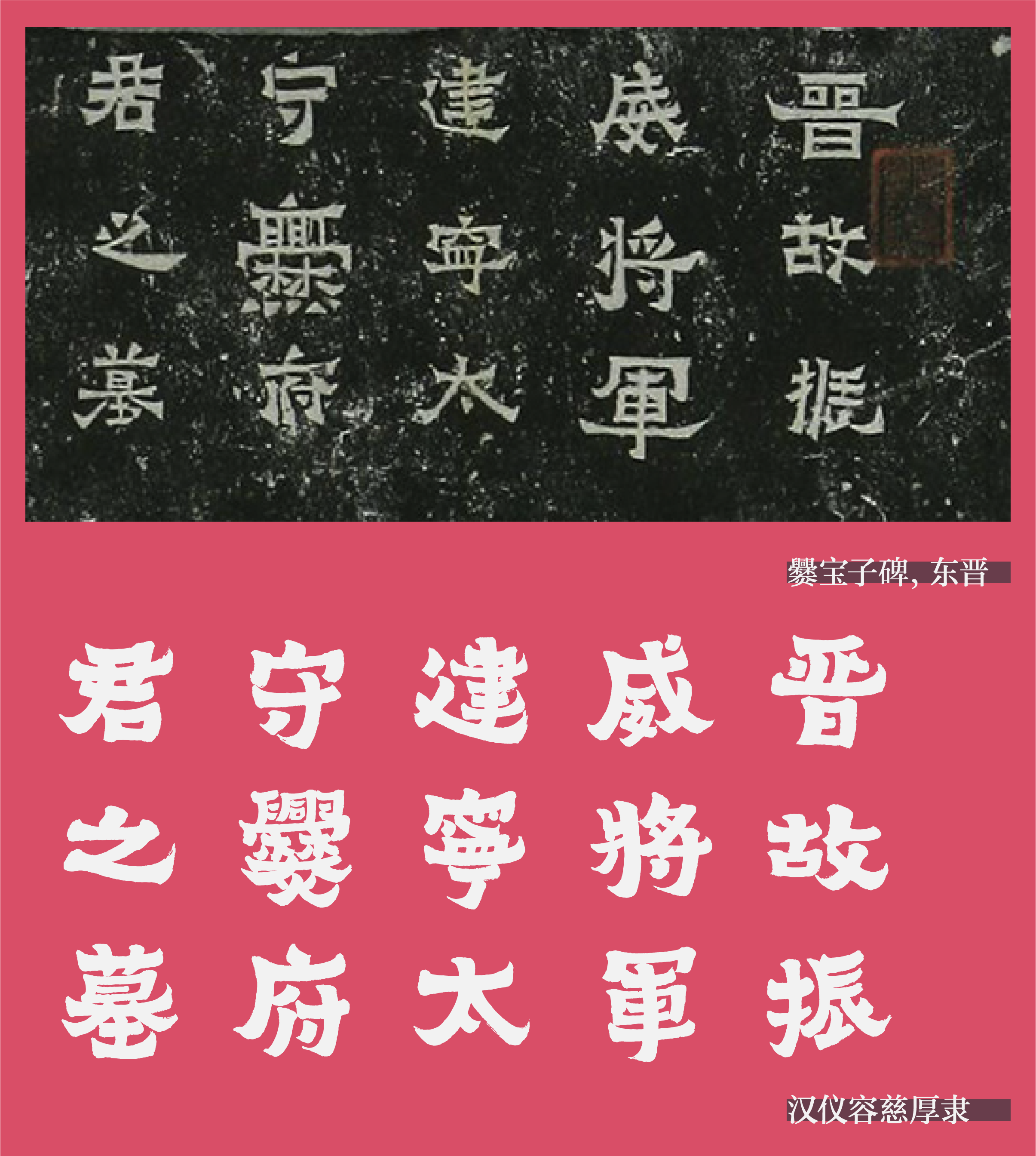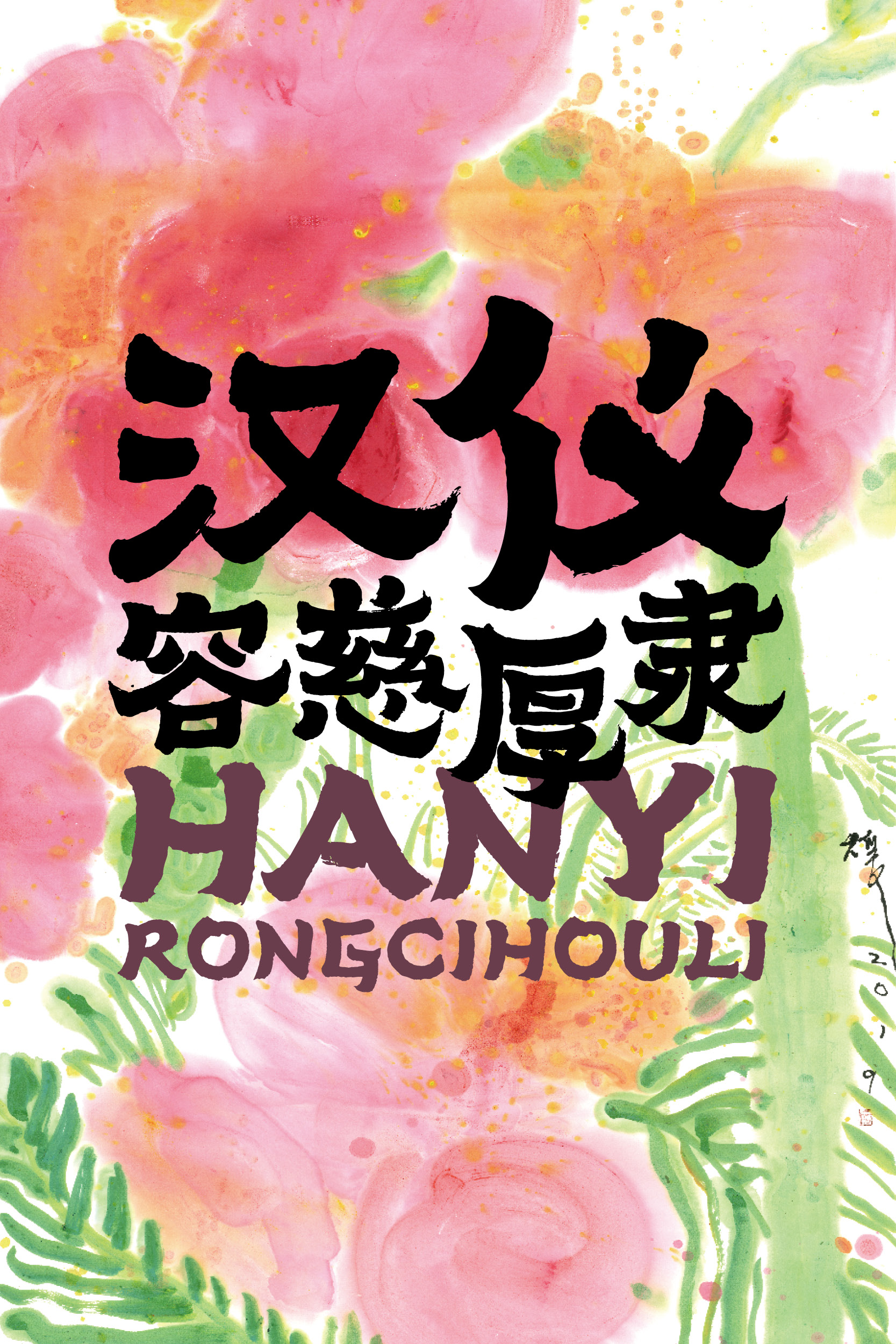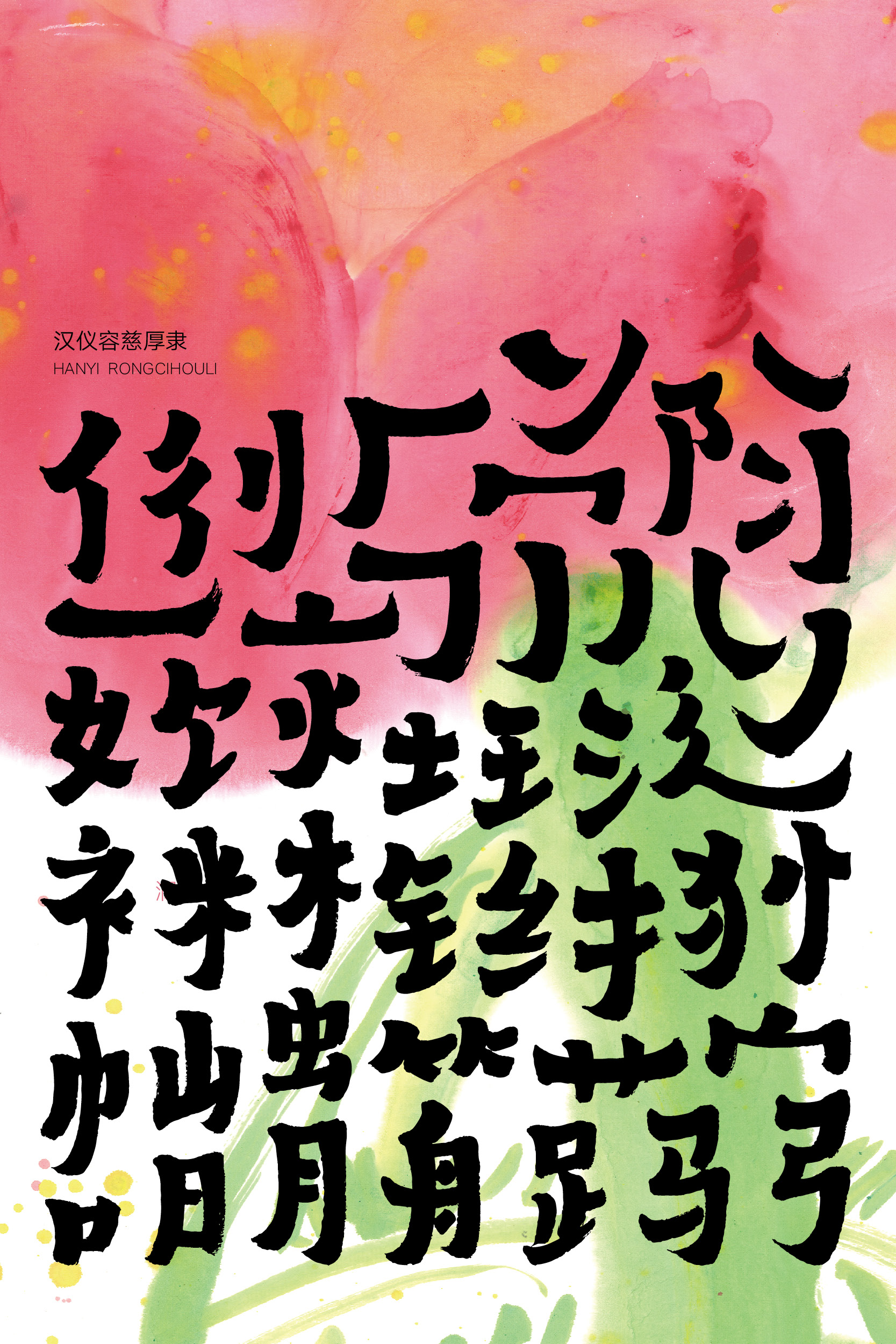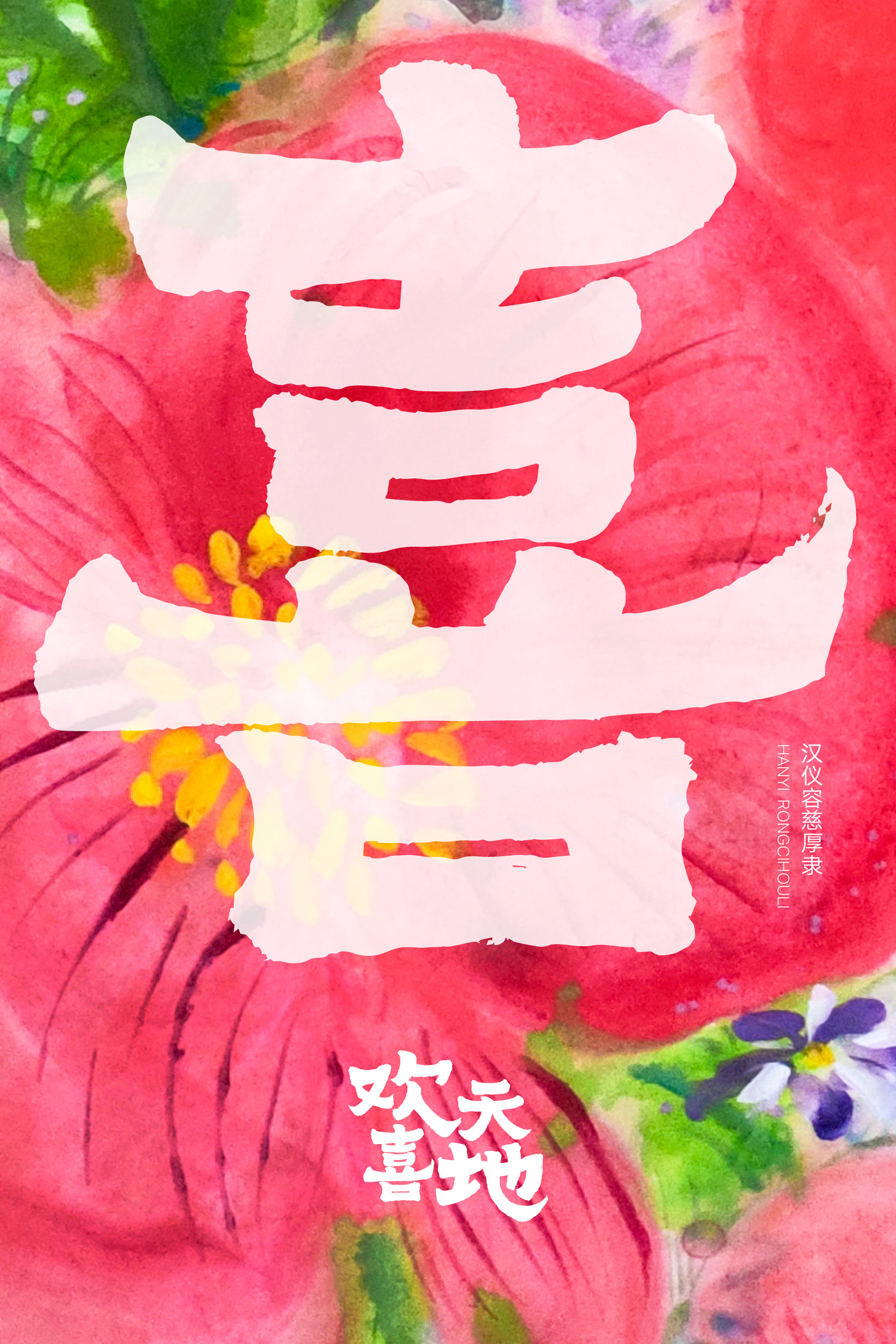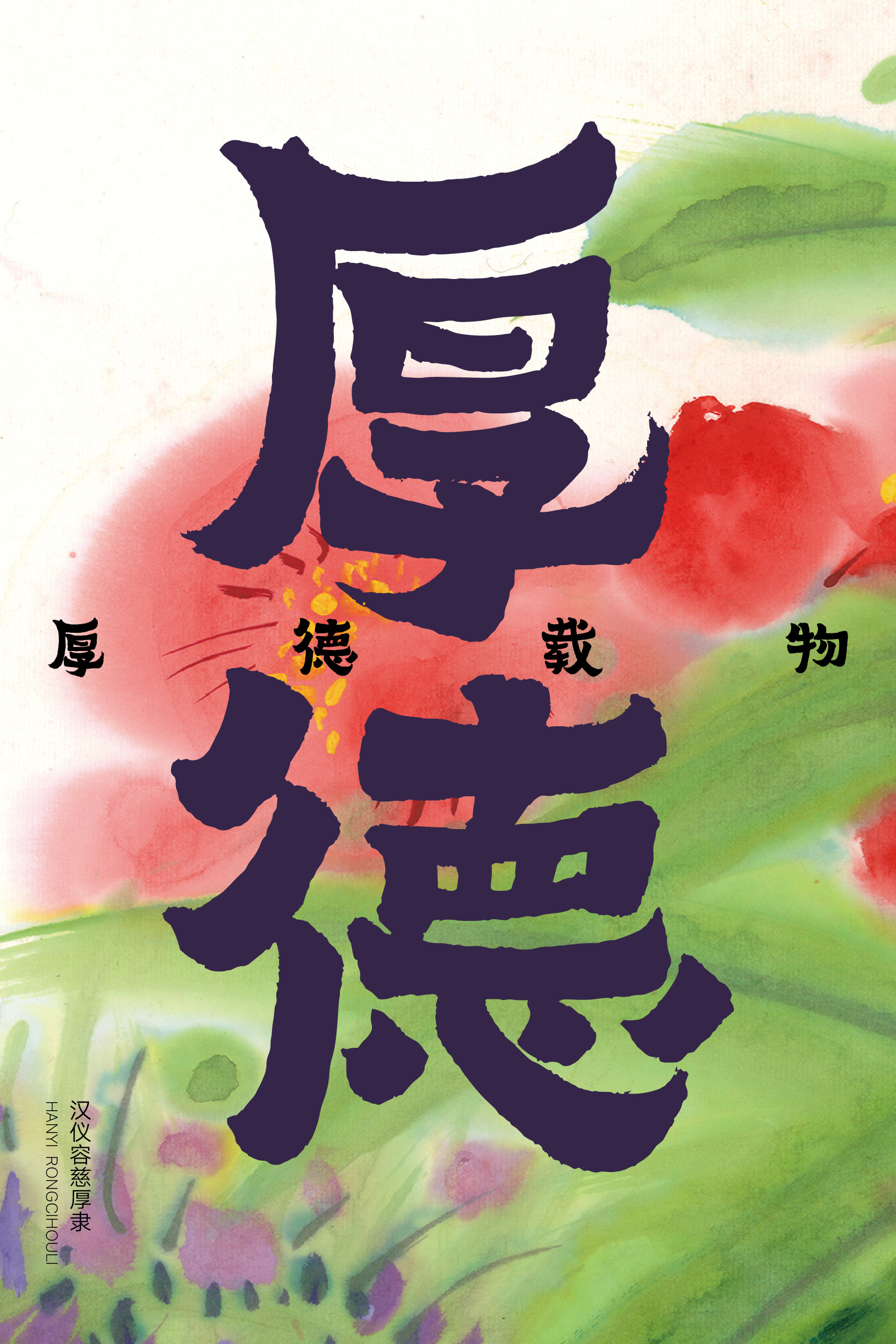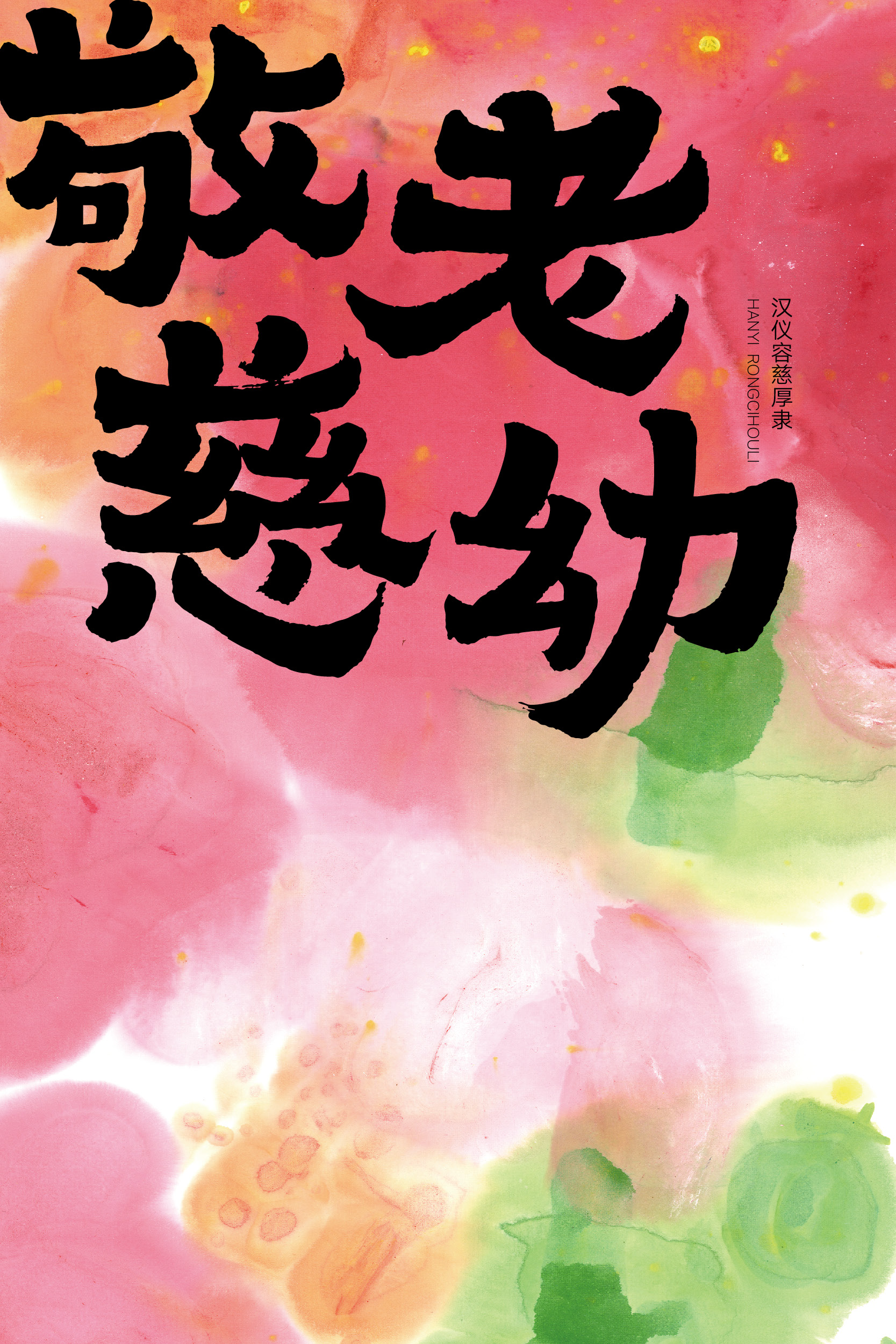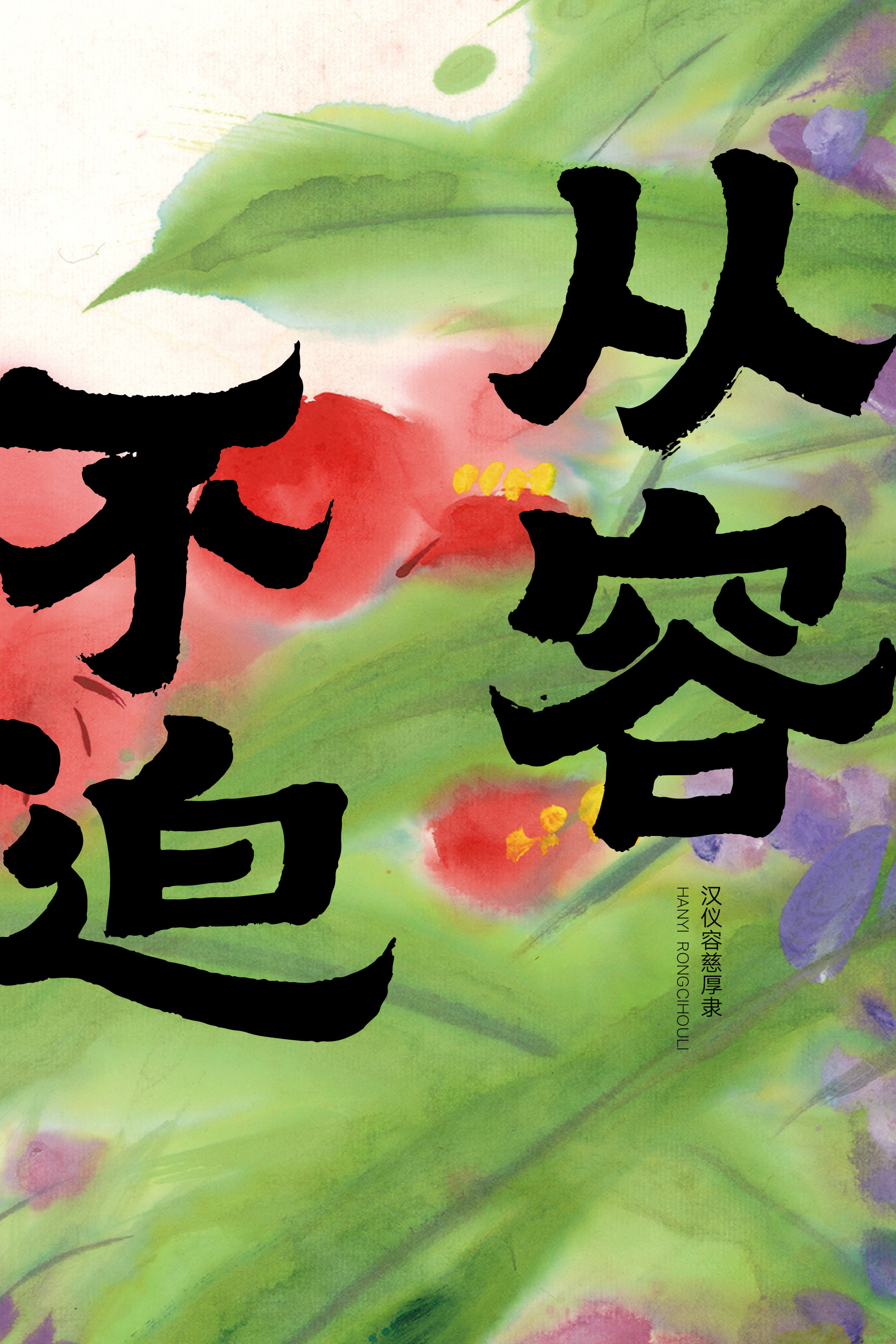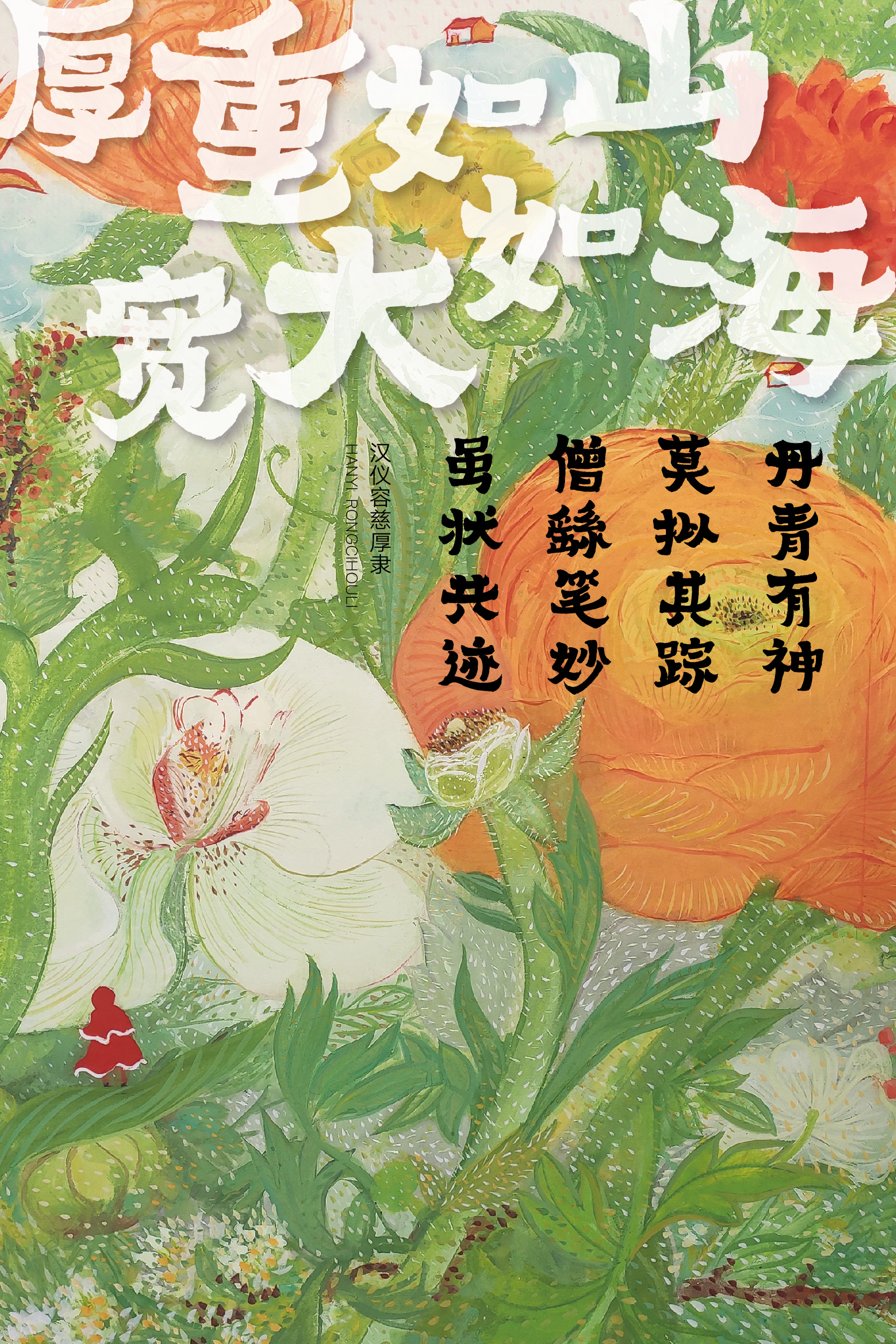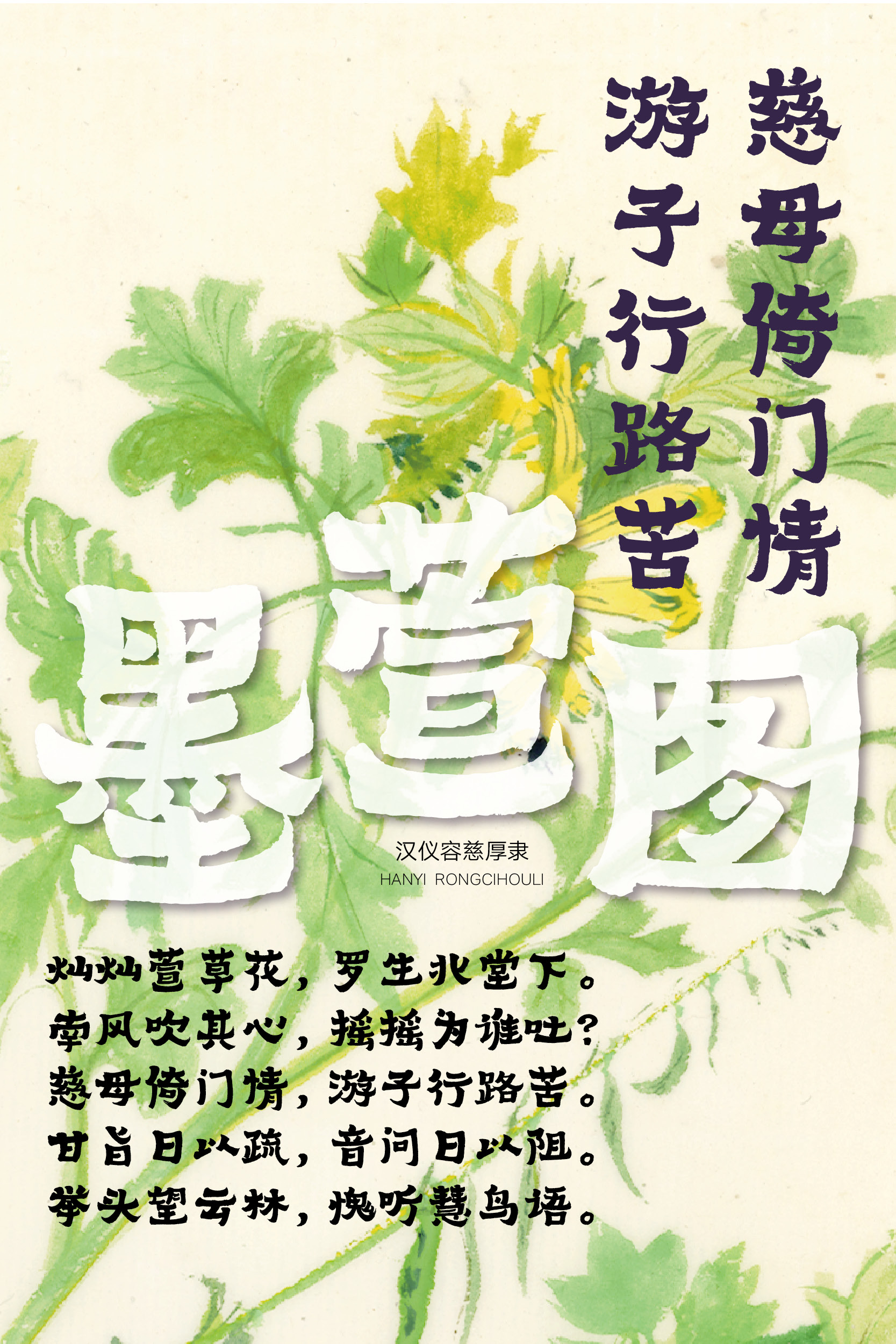
汉仪容慈厚隶
汉仪容慈厚隶是一款氛围温暖朴厚而蕴含着浓浓禅意的隶书书法字体。这款字体间架结构源自云南爨宝子碑,并取张迁碑的率真与厚重,融合民间质朴之风。字形寓巧于拙,呈扁势;笔画温厚朴实。汉仪容慈厚传达了温和朴厚的温暖氛围和清寂安宁的禅意古趣,表现出活泼的生活气息,适用于艺术展览、画册书籍、广告包装、休闲娱乐等各种使用场景。
汉仪容慈厚隶的间架结构源自东晋时期的云南爨宝子碑。该碑结体介于隶楷之间,朴拙怪诞而颇具生气,古朴康有 为评曰:“端朴若古佛之容”,“朴厚古茂,奇姿百出”。
并取张迁碑的率真与厚重,融合民间质朴之风。
字形寓巧于拙,呈扁势。
笔画温厚朴实,方笔起笔厚重,收笔末端扬起。
汉仪容慈厚隶的西文部分取朴拙质朴的书写风格,充满禅意古趣,与中文搭配使用可以满足更多使用场景的需要,传达温暖的氛围。